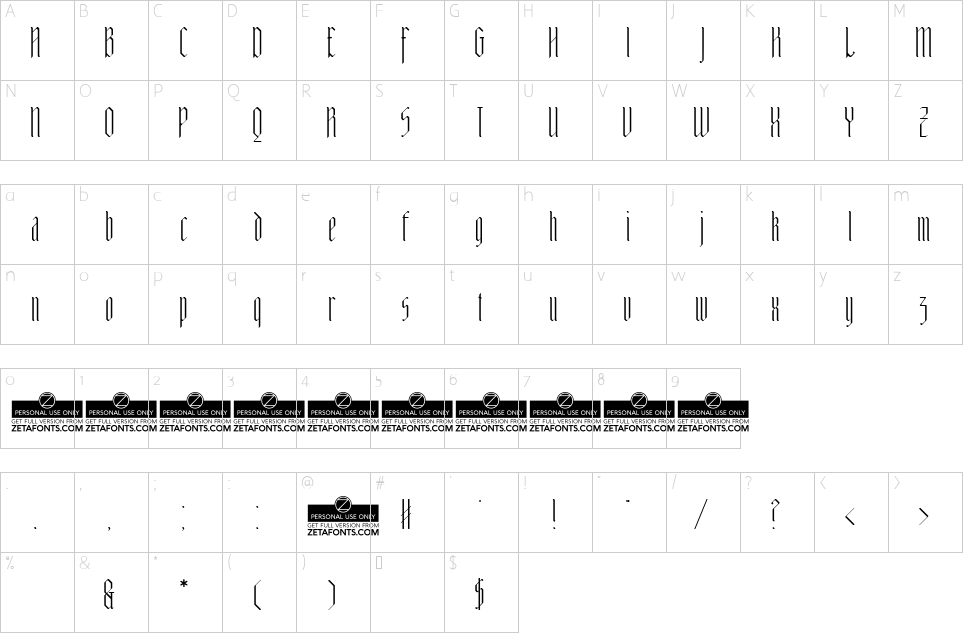
Aqui está uma descrição em português para a página de download da fonte Adlibitum: A Adlibitum é uma elegante fonte criada por Zetafonts. Seu design clássico e sofisticado torna-a perfeita para gráficos e publicações de alta qualidade. Oferecida gratuitamente, esta fonte atinge 51.464 downloads, demonstrando sua popularidade entre designers e profissionais de gráfica. Ideal tanto para textos legíveis quanto para gráficos, a Adlibitum oferece um toque de elegância em qualquer projeto. Experimente a Adlibitum e descubra por si mesmo por que essa fonte é uma escolha inteligente para seus projetos digitais.